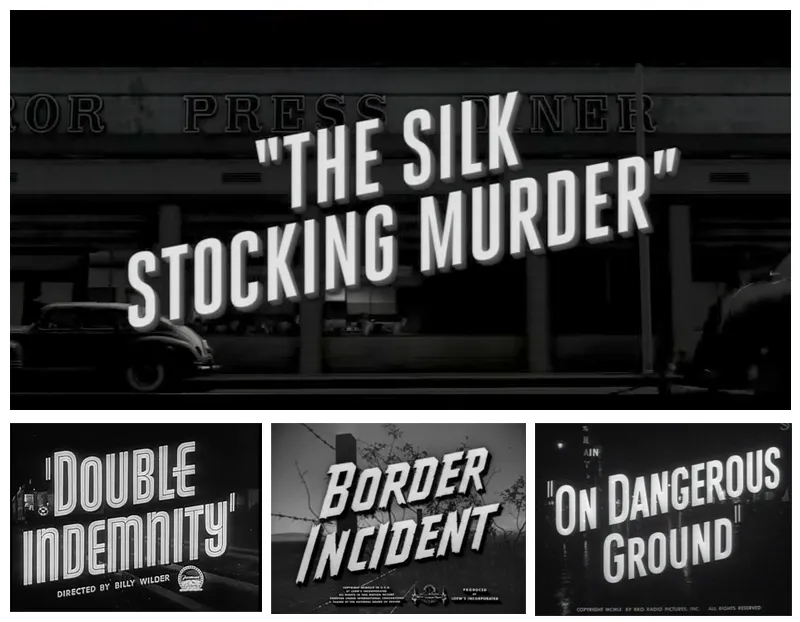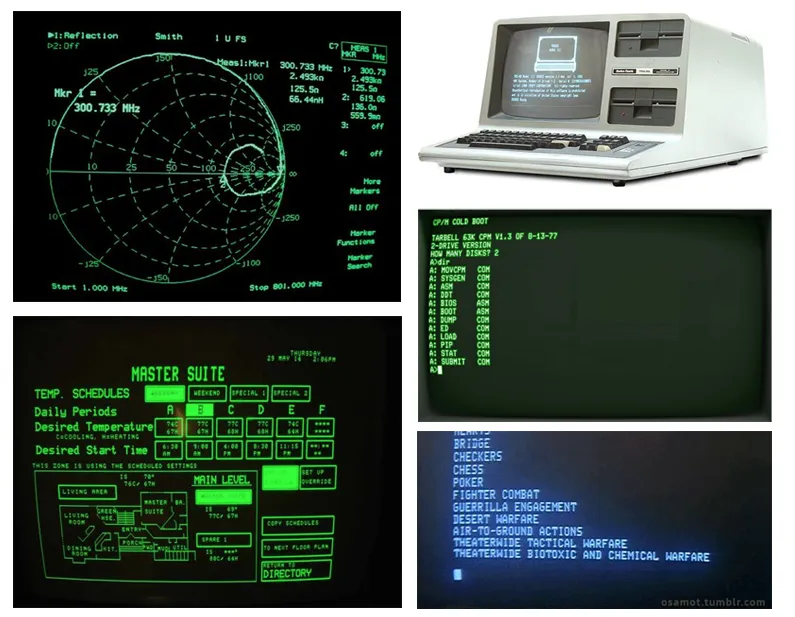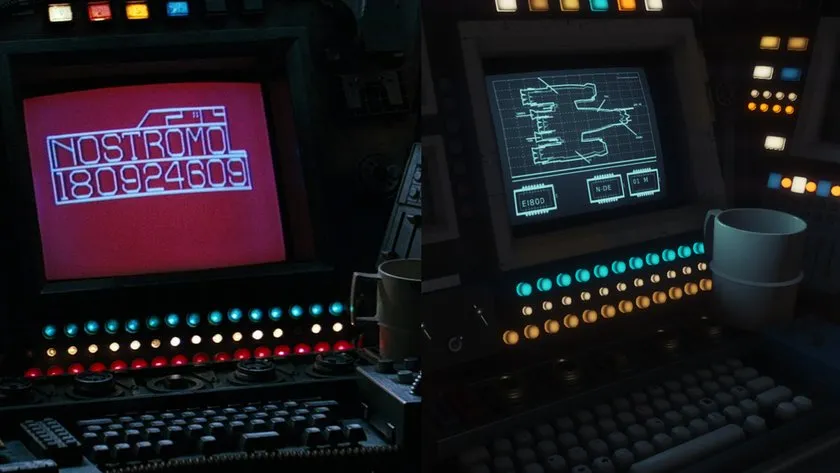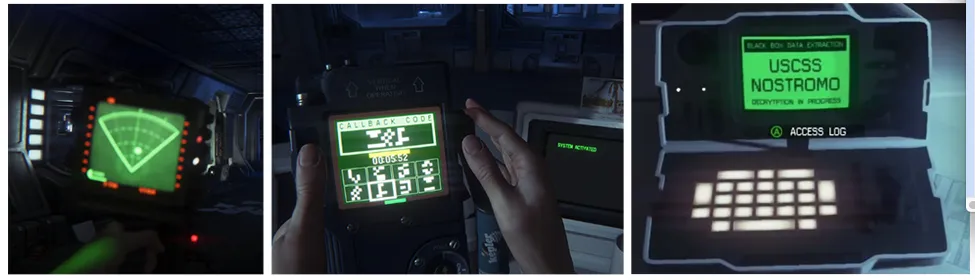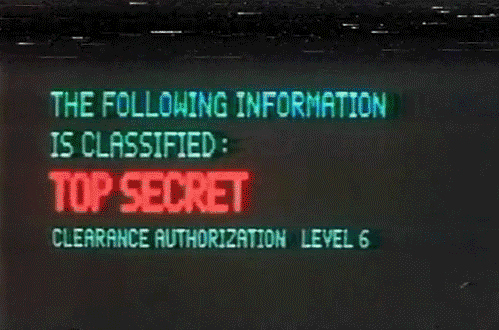
在电子游戏开发中,美术指导是一项确保整体风格统一的关键工作。从角色、场景到 UI,每个元素都需要协调一致,才能构建出有说服力的世界观。
恰到好处的字体选择,不仅提升整体美感,更能强化时代感、故事性与互动真实感,让玩家更深地沉浸于游戏世界之中。
本篇将通过时代设定、拟真空间、系列作品三个不同角度,探讨字体是如何让游戏世界更具说服力与吸引力的。
唤醒时代记忆
英雄连2
二战题材一直是游戏常见设定,维基百科上列出的相关作品就有百余款,涵盖《使命召唤》这类射击游戏、《钢铁雄心》这类策略游戏,或《盟军敢死队》等动作冒险游戏。这些作品在字体运用上手法相近,但真正做到视觉统一且极具时代感的,当属《英雄连2》。
《英雄连2》是一款极受欢迎的线上即时战略游戏,图为游戏画面。作为一款 PC 即时战略游戏,《英雄连2》的 UI 设计细致入微:装弹带加载条、勋章图标、战地地图与军用文书等元素融合,辅以专业的字体设计,共同还原了真实的战争氛围。
接下来,我们将具体看看,这款游戏如何通过字体强化其二战美术风格。
主菜单画面,抽象风格的 UI 融合了契合主题的视觉元素。如下图所示的加载画面中,可以看到装弹带式的加载条位于下方,中央则是文件夹与打字机风格的任务简报。这种拟真化处理有效营造了游戏氛围,而字体 Hermes 的运用更是强化了这种设定感。
放大后的加载画面,展示了所使用的字体 Hermes。Hermes 字体在 1940 年代初被广泛用于报纸和各类出版物,当时的大多数可读材料都需通过印刷或打字完成。Hermes 及其相似字体几乎是当时打字机和打印设备的标准配备,而这些设备也正是军方用来制作任务简报和各种文件的工具。
因此,在《英雄连2》中阅读任务简报时,这款字体的运用不仅具有真实感,也在视觉上准确还原了那个时代的氛围。
二战时期的任务报告、一份尚未解密的电文备忘录,以及一台使用 Hermes 字体的 Underwood 打字机。通过采用 Hermes 字体,游戏开发者成功地在游戏世界之外也延续了二战的主题感。这正是一个很基础但有效的例子,说明恰当的字体选择如何显著提升特定时代背景下的美术表现力。
模拟真实空间
黑色洛城
2011 年 Rockstar 推出的《黑色洛城》背景设定在 1940 年代的洛杉矶,玩家扮演侦探,探索开放世界,调查案件、收集线索并审讯嫌疑人。游戏采用当时领先的面部表情捕捉技术,帮助玩家通过观察嫌疑人的反应判断其是否说谎,增强了审讯的真实感。
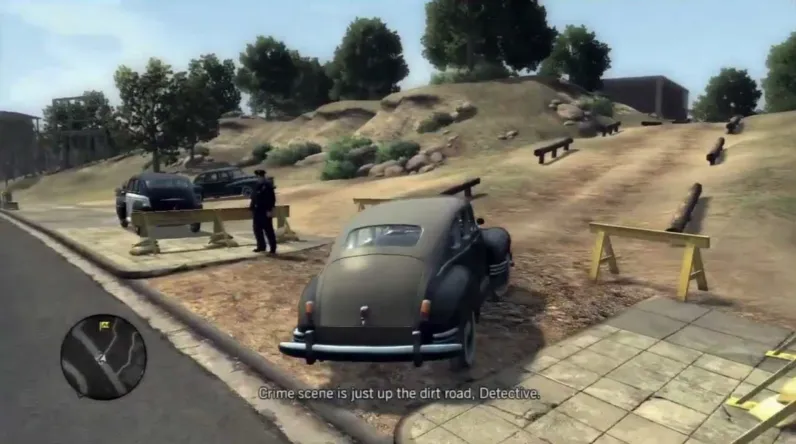
随着游戏推进,玩家会将线索、不在场证明,甚至嫌疑人的肢体语言等信息记录在笔记本中。而这正是字体强化拟真设计的地方:所有笔记都以铅笔手写风格呈现,增强了沉浸感。
这种独特的铅笔风格字体,让玩家更容易在笔记中识别和回忆线索。而铅笔笔迹本身的不确定感,也巧妙传达了信息的模糊性:它们可能是谎言、误导,或毫无价值的死路。
题外话:当然,少数情况下游戏故意传递不准确的信息,反而产生了惊艳的效果。比如 N64 上的哥特恐怖游戏《永恒的黑暗》(Eternal Darkness),主角会随着剧情逐渐失去理智,游戏中穿插各种「理智崩溃」效果:屏幕上爬满假蚂蚁、虚假的蓝屏死机,甚至还有一段恶意模拟系统提示,假装正在删除玩家的存档。
《黑色洛城》的第三人称自由探索场景,画面中可见字体的呈现方式。
上图:游戏《黑色洛城》的片头标题;下图:多部 20 世纪 40 年代电影的真实片头画面。而最具美术指导巧思的,是每宗案件开场时的标题设计:每起案件都有专属的名称和片头动画,致敬了 20 世纪 40 年代的黑色电影风格。
延续系列设定
异形:隔离
Creative Assembly 备受好评的作品《异形:隔离》《异形:隔离》(2014)是一款生存恐怖游戏,续写了 1979 年电影《异形》的故事。玩家电影主角艾伦·里普利的女儿阿曼达,调查母亲所在的失事宇宙货船诺斯特罗莫号。游戏时间设定紧接电影剧情,视觉风格高度一致,营造出紧密衔接的世界观。
《异形》剧照:艾伦·里普利在宇宙货船诺斯特罗莫号主甲板上。开发团队 Creative Assembly 面临一个特殊挑战:他们要制作一款 2014 年发行的游戏,作为 1979 年科幻电影的续作,而故事背景设定在 2104 年。这样的时间跨度不仅难以解释,也让美术创作变得异常复杂。
为此,美术总监制定了一套严格的规则来指导设计。游戏中不会出现 1979 年原电影布景里无法存在的元素。游戏中的一切都遵循复古未来主义美学。
游戏美术团队还在必要时直接借鉴了电影中的道具,确保游戏与电影世界紧密对应。这种复古未来主义的理念贯穿于角色、场景、道具,当然也包括用户界面的美术指导。
70 年代末到 80 年代的各种 HUD 图形和界面示例,可以看到当时的字体设计非常简洁。《异形:隔离》中的主角会操作多种采用 CRT 屏幕的电脑界面,风格忠实还原了原电影中的道具。这些界面采用简洁的 HUD 设计和基础的电脑显示布局,体现了当时设计师眼中最先进的计算机技术。
采用复古风格,团队摒弃了现代高端技术,如视网膜屏幕和动态图形,还必须选用与低保真科幻风格契合的字体。
左图为电影中 Nostromo 主甲板的电脑界面,右图为游戏中 Sevastopol 号上的相应设计。
游戏中你会接触到的各种界面。